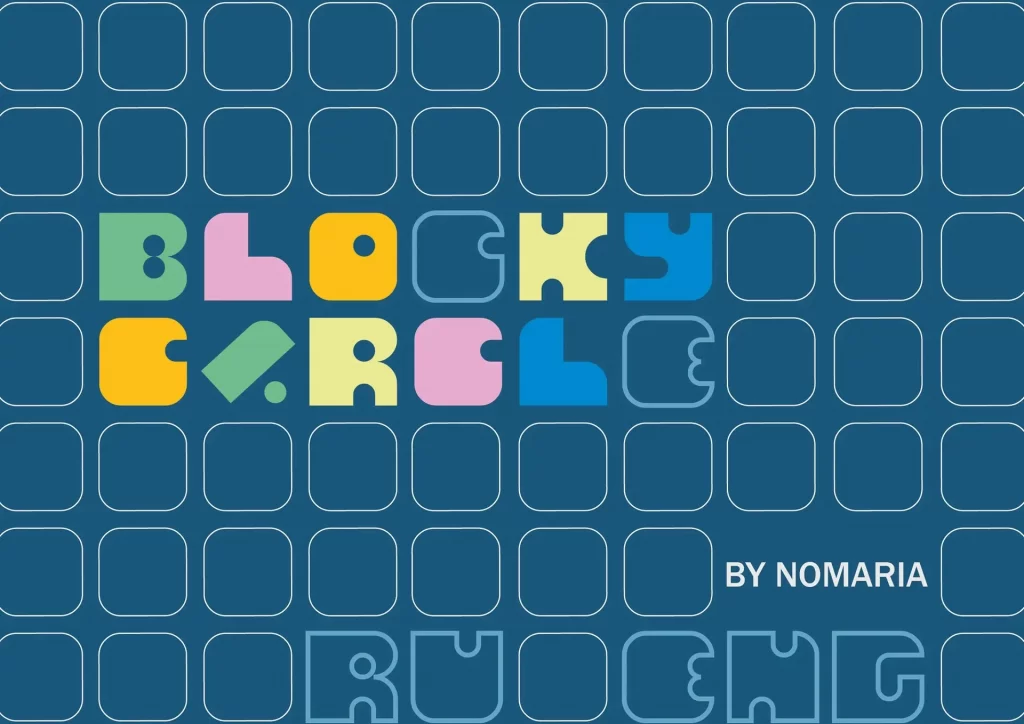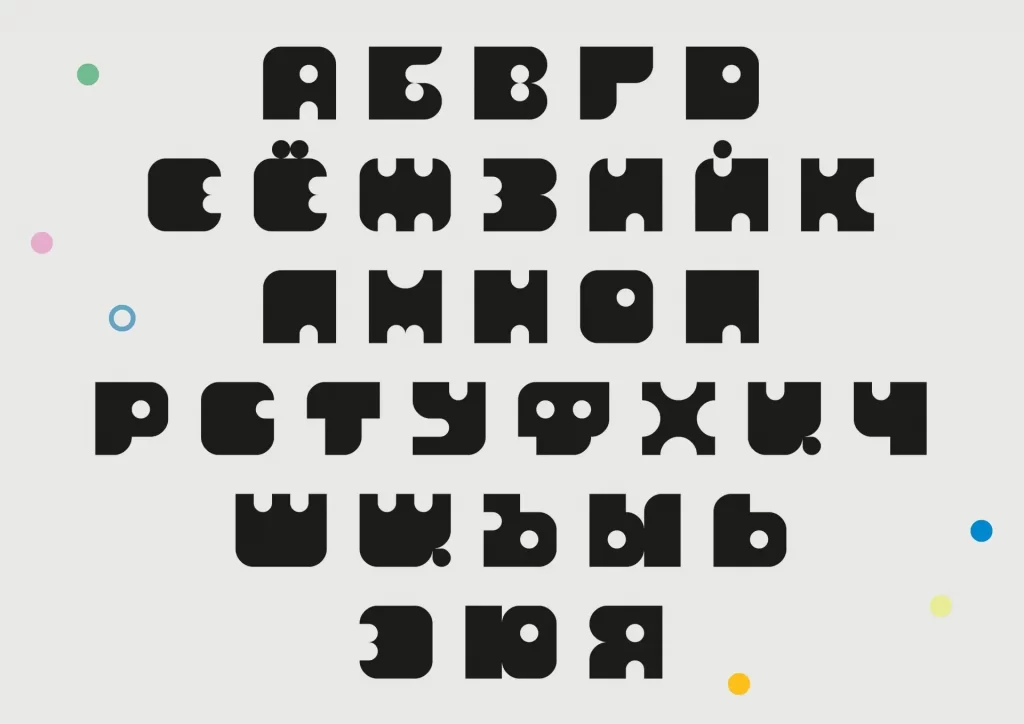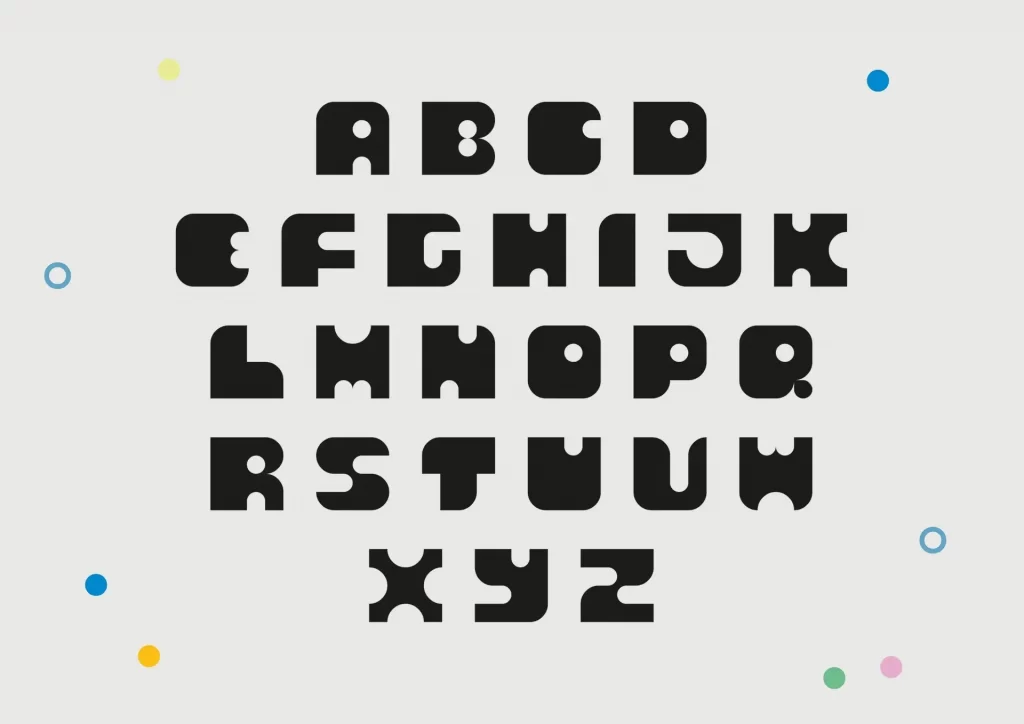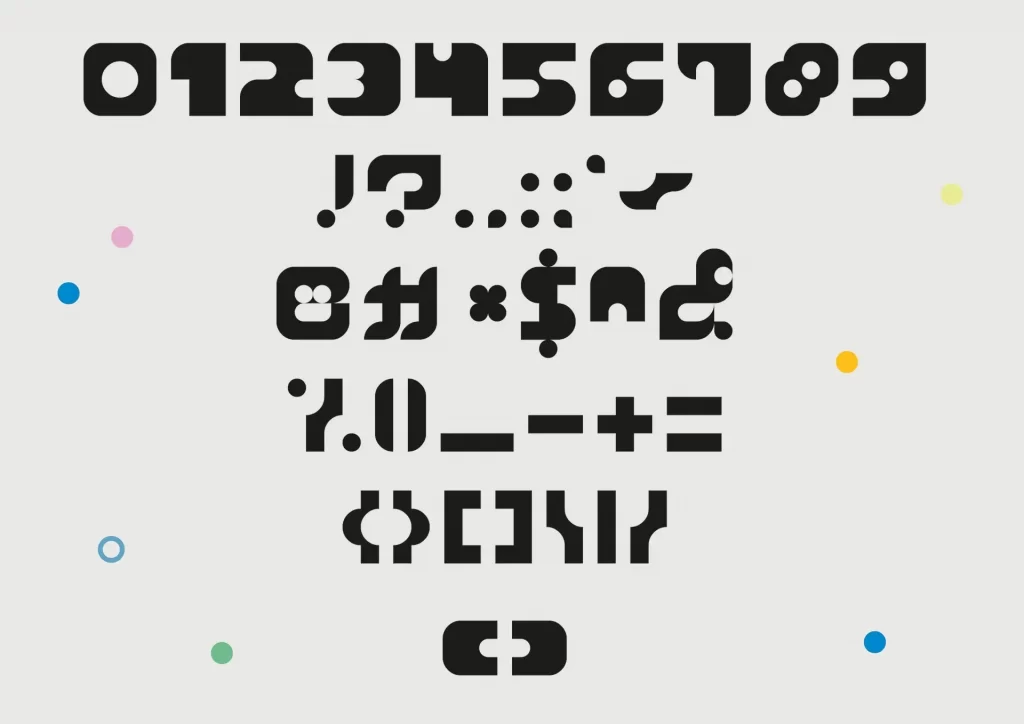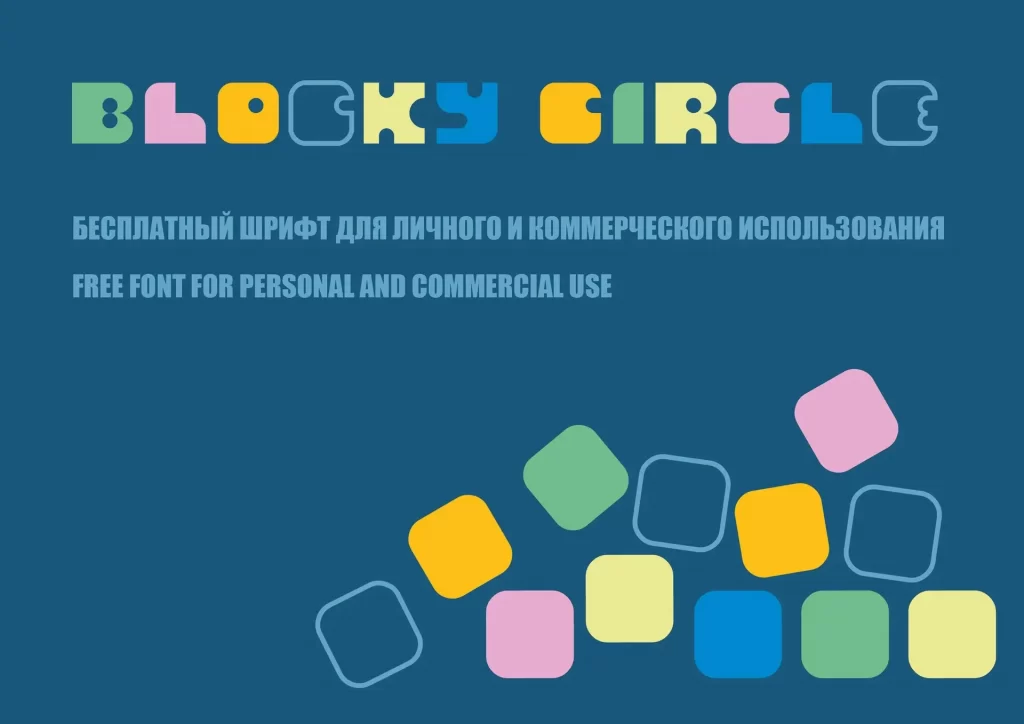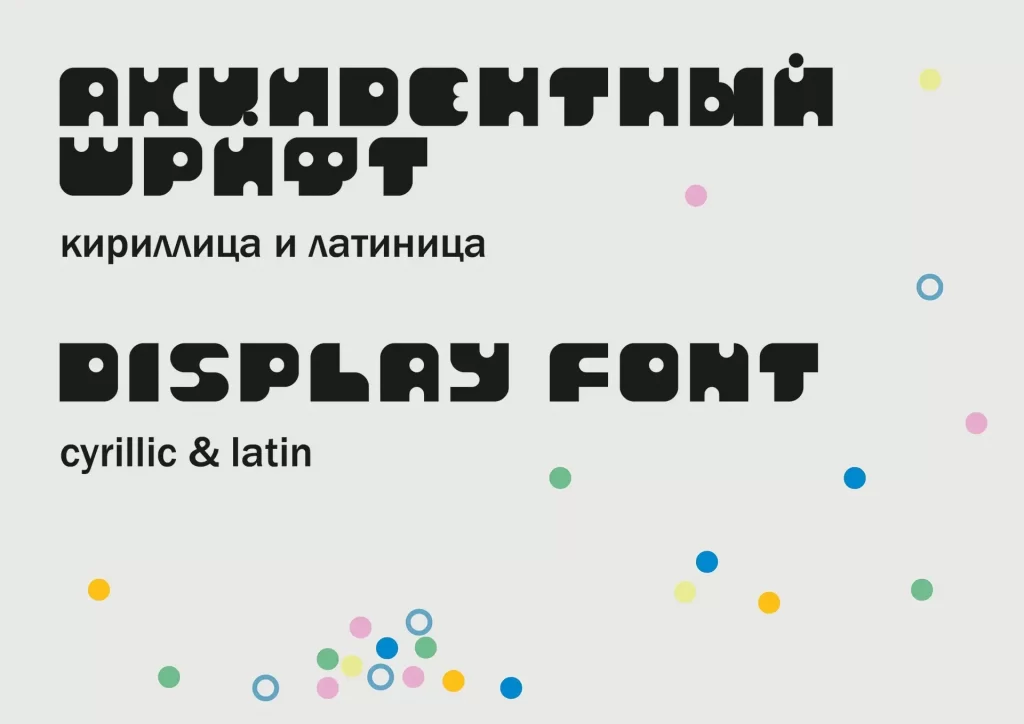
Blocky circle — забавный шрифт с поддержкой кириллицы
Blocky Circle — модульный геометрический декоративный шрифт, созданный из простых форм и игровых принципов конструктора. Каждая буква сочетает в себе массивные блоки и мягкие округлые элементы, создавая уникальный баланс между структурированностью и игривостью.
Благодаря выразительности и визуальной силе, Blocky Circle идеально подходит для броских заголовков, современных постеров, креативного брендинга, обложек альбомов и эффектных макетов. Его яркая, основанная на формах индивидуальность делает его отличным выбором для проектов, которым важны оригинальность, современность и лёгкость.
С комбинацией геометрии и живого характера Blocky Circle привносит в любой дизайн свежий, энергичный и неповторимый голос.